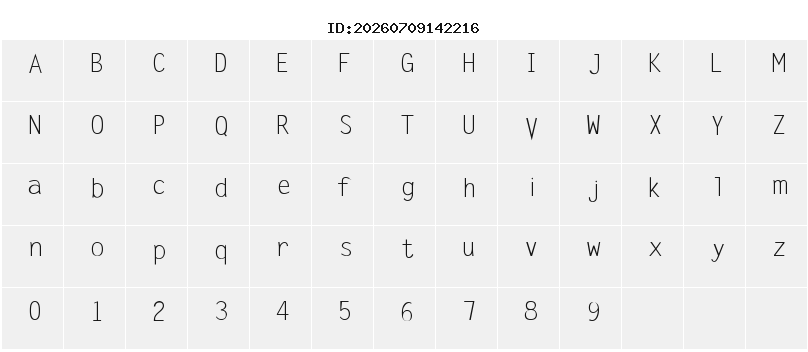
字体家AI造字特隶 Preview
• Font Name: 字体家AI造字特隶
• Description: 这是一款非常具有个性的AI字体,有隶书的风骨在汉字的一种外柔内刚的美的线条和结构。
About 字体家AI造字特隶.ttf
字体家AI造字特隶.ttf is a modern, elegant sans-serif font designed for ultimate readability and visual harmony. Perfect for branding, headlines, web design, and print materials.